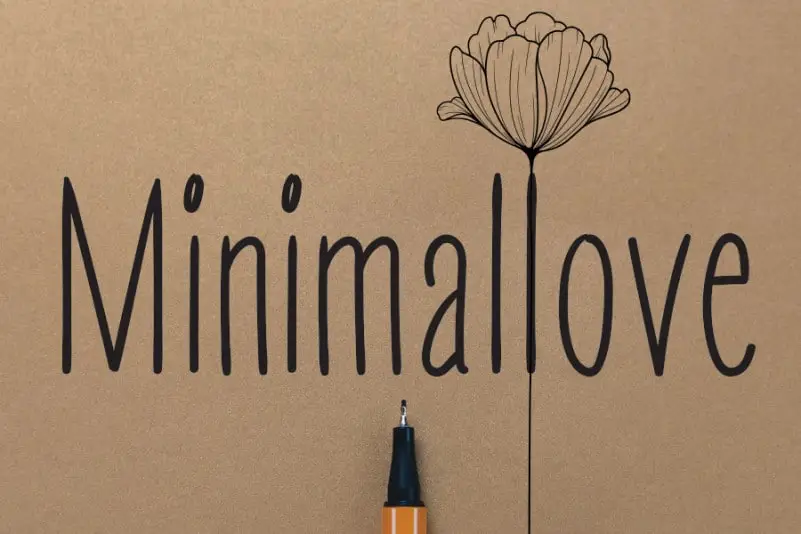
Minimallove Handwritten Font
A fonte ‘Minimallove Handwritten Font’ é uma delicateza cuidadosamente elaborada, que combina simplicidade com a autenticidade única do estilo manual. Suas linhas finas e elegantes têm um toque natural que os torna ideais para vários projetos de design, desde logos simples até cartões personalizados. Seu único limite é sua criatividade, permitindo-lhe criar designs únicos em uma grande variedade de ambientes gráficos. Com ‘Minimallove Handwritten Font’, deixe seu design fluir livremente, aproveitando todo o poder da fonte para expressar suas ideias e personalidades. Experimente agora e descubra a diferença que este único estilo pode fazer no seu trabalho.